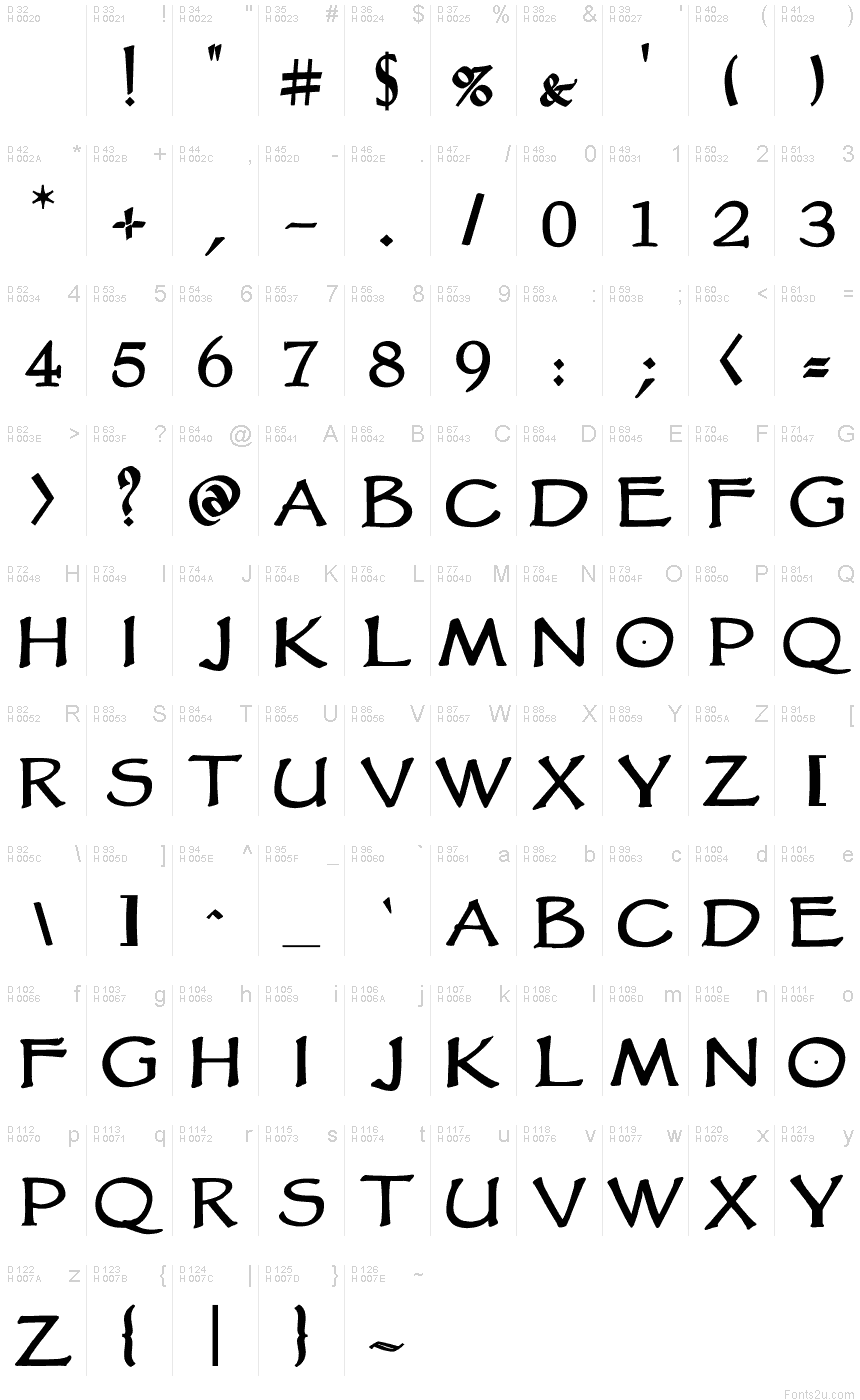
VTC Goblin Hand Bold, di VTC Vigilante Typeface Corporation, è un font display gratuito con l'atmosfera storta di un libro di fiabe. Le lettere si basano su tratti irregolari e affusolati con estremità smussate e corpulente, mescolando l'arte delle insegne medievali con un'irregolarità artigianale maliziosa che rende le maiuscole vivaci piuttosto che formali.
È perfetta per copertine di libri fantasy, locandine di Halloween, titoli di giochi, copertine di fanzine e per il branding di pub o eventi in cui un tocco folcloristico e grezzo aiuta a creare l'atmosfera giusta. Essendo un font gratuito, funziona bene anche per titoli brevi, incipit di capitoli e monogrammi, poiché le lettere hanno abbastanza carattere e asimmetria da reggere il confronto da sole.